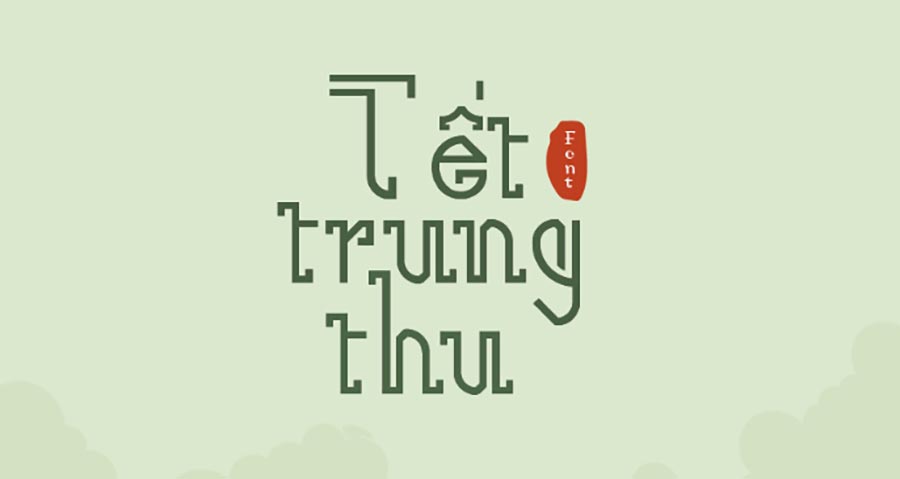
Chia Sẻ Miễn Phí Font Line Phone Việt Hóa - Bộ Font Chữ Cho Trung Thu
Trong thời đại số hóa hiện nay, việc sử dụng các font chữ sáng tạo và độc đáo đã trở thành một phần không thể thiếu trong thiết kế đồ họa, đặc biệt là trong các dịp lễ hội truyền thống như Trung Thu. Để đáp ứng nhu cầu này, sadesign.vn đã chia sẻ miễn phí bộ font Line Phone Việt Hóa, mang đến sự lựa chọn hoàn hảo cho các nhà thiết kế và người dùng yêu thích sáng tạo.
Điểm Nổi Bật Của Font Line Phone Việt Hóa
Font Line Phone là một bộ font chữ được thiết kế với phong cách hiện đại, tối giản nhưng không kém phần ấn tượng. Với việc Việt hóa hoàn chỉnh, bộ font này hỗ trợ đầy đủ các ký tự tiếng Việt, giúp người dùng dễ dàng sử dụng trong các dự án thiết kế liên quan đến văn hóa Việt Nam.
Những đặc điểm nổi bật của font Line Phone bao gồm:
1. Thiết Kế Tối Giản Và Hiện Đại: Font chữ được thiết kế với đường nét gọn gàng, tinh tế, phù hợp với nhiều phong cách thiết kế khác nhau.
2. Hỗ Trợ Tiếng Việt Hoàn Chỉnh: Font đã được Việt hóa để đáp ứng nhu cầu sử dụng trong các dự án thiết kế nội địa.
3. Phù Hợp Với Dịp Trung Thu: Với sự kết hợp giữa nét truyền thống và hiện đại, font Line Phone là lựa chọn lý tưởng để tạo nên các ấn phẩm như thiệp mời, poster, hoặc banner cho mùa Trung Thu.